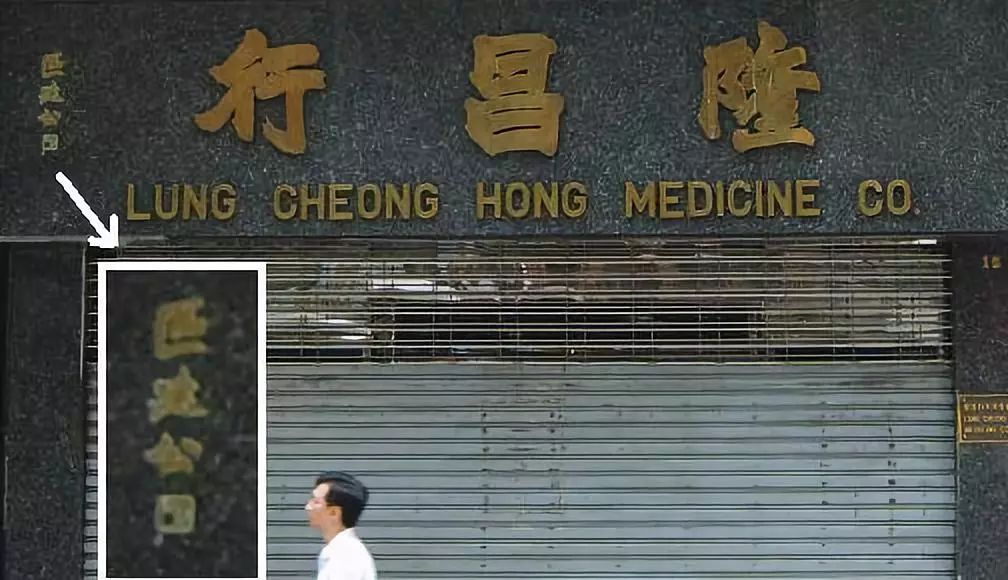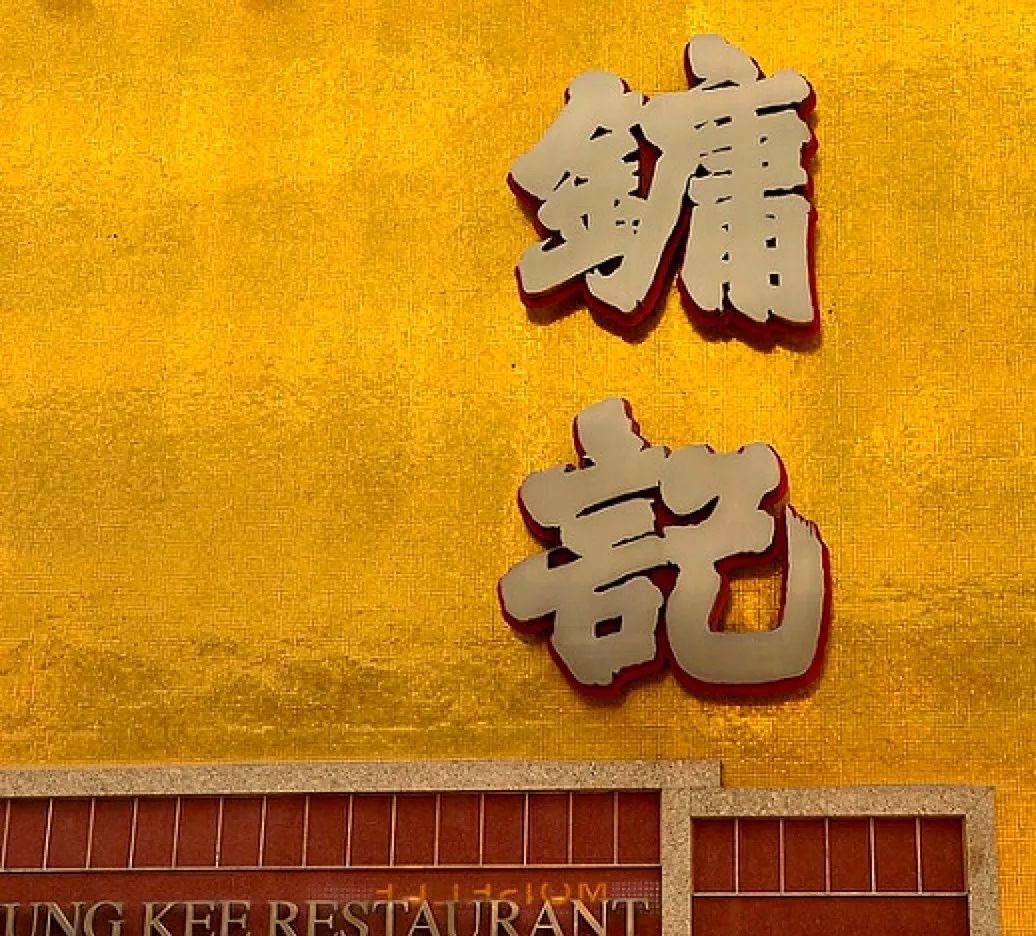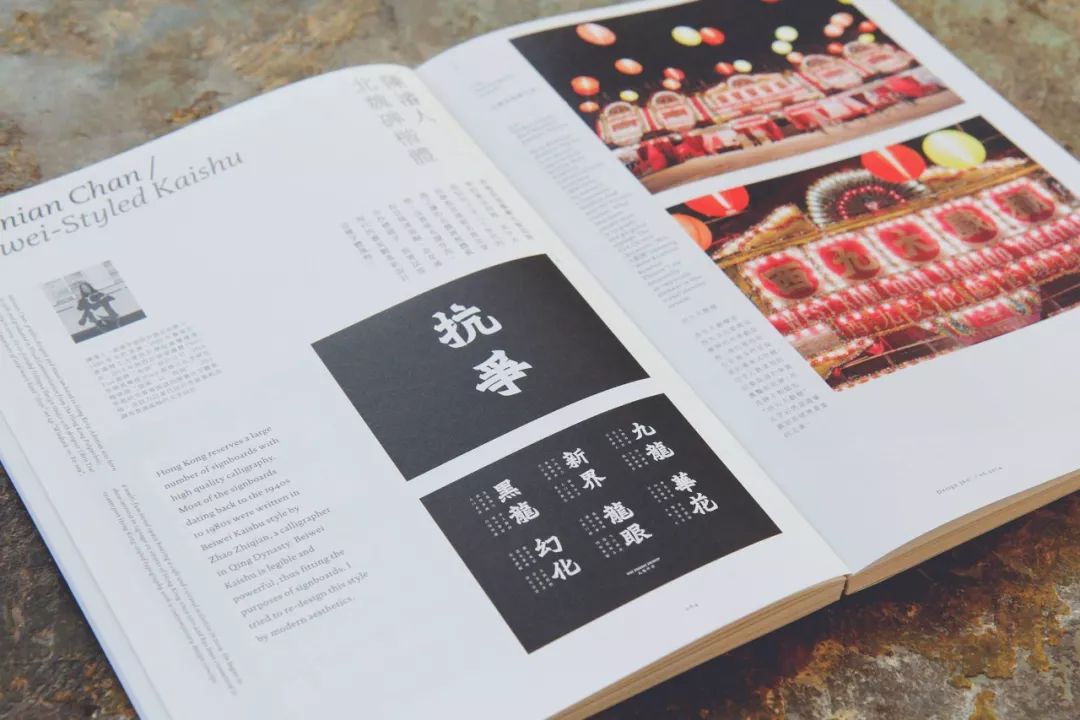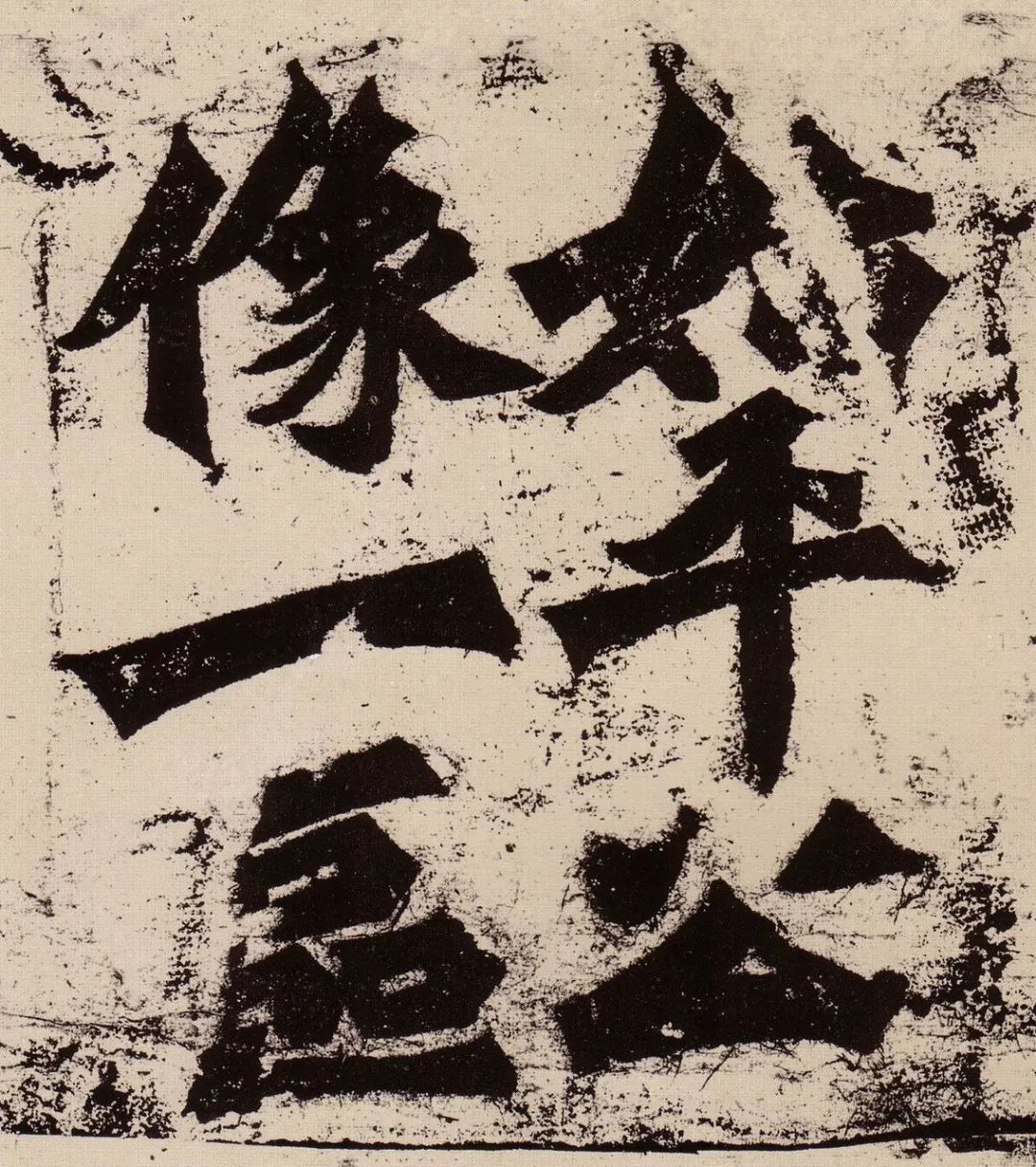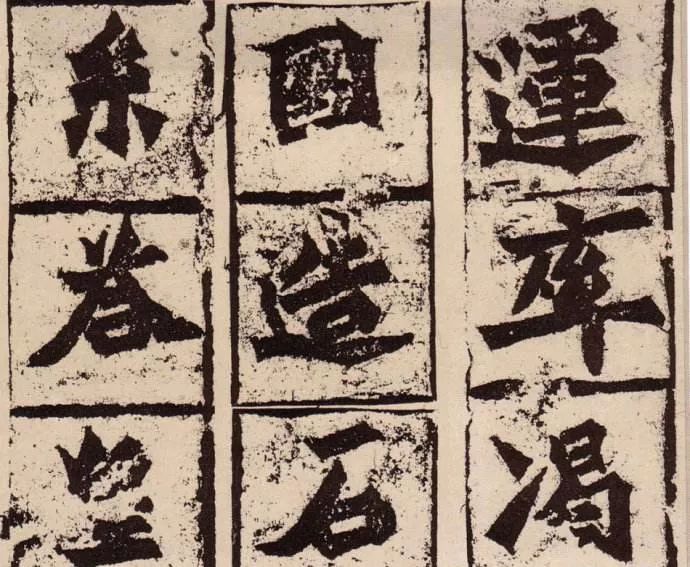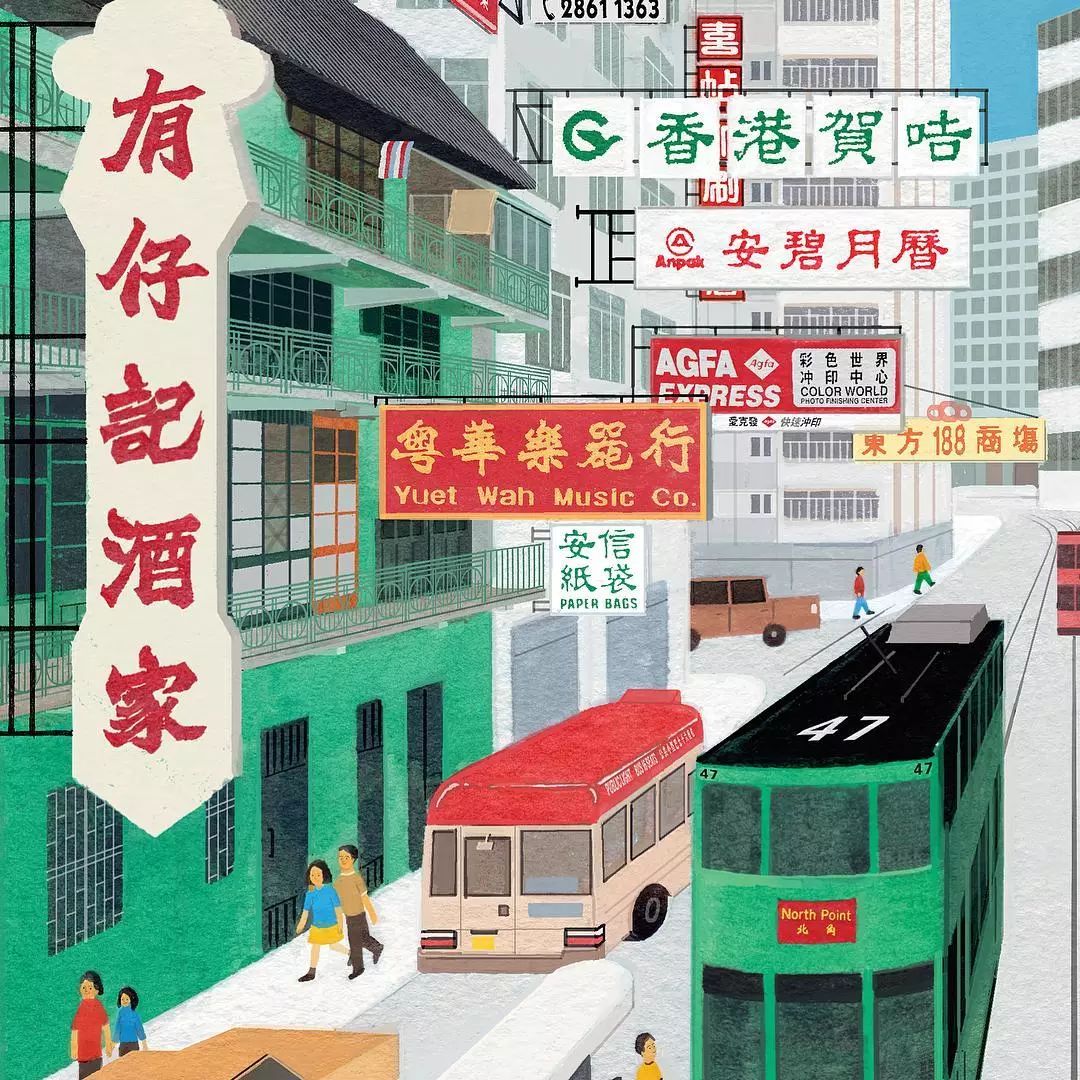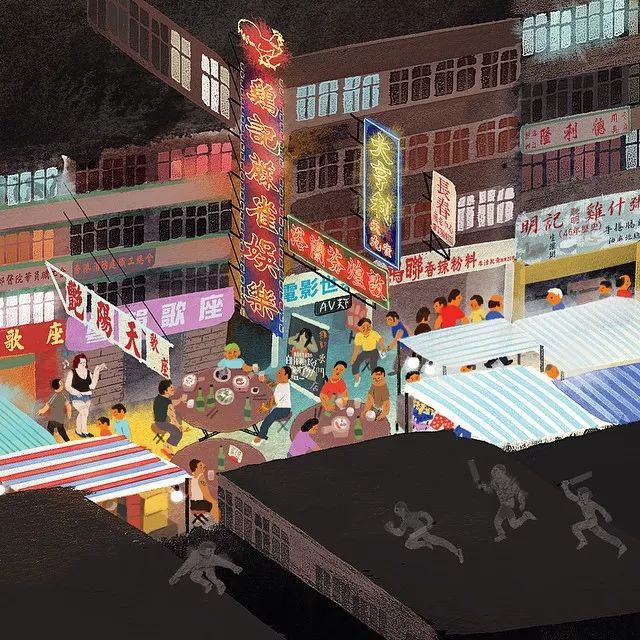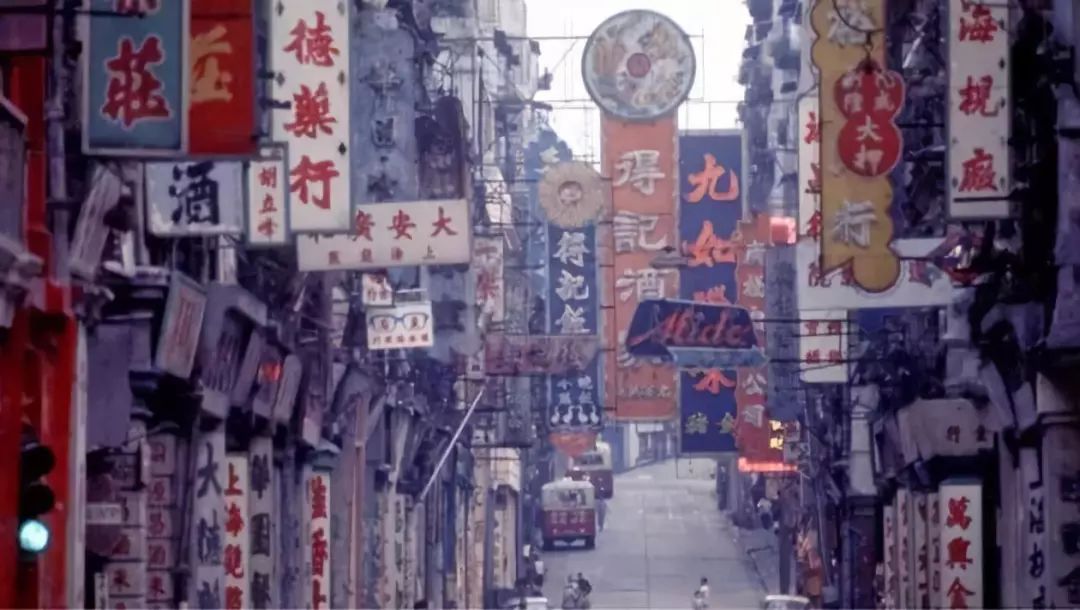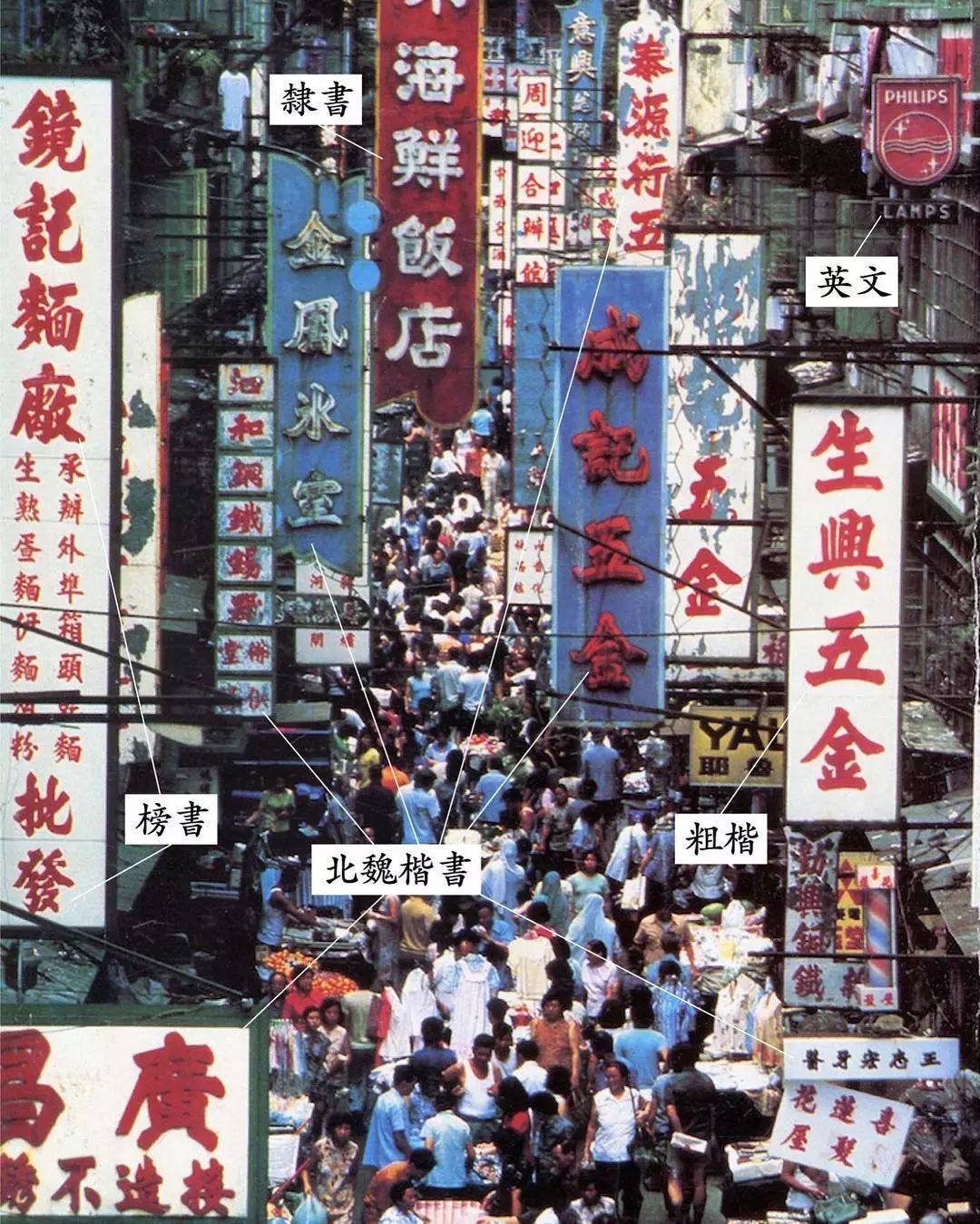
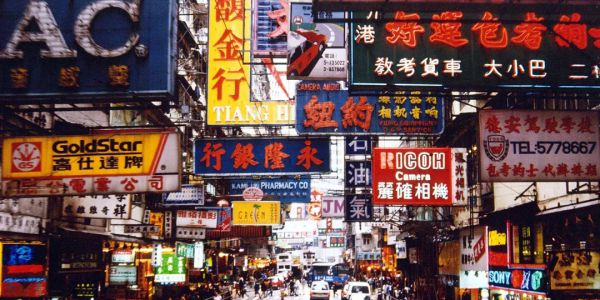
这种字体,曾经风靡了全香港
香港是招牌之都,当你在旧区四处张望,头上总有一两个书法、霓虹招牌。追根寻源,反寻到古字宝藏,香港独有的北魏楷书字体在街招上发扬光大,流传数十载,形成独有街头美学及庶民文化。如今,无处不在的笔迹随市区重建,老铺倒闭,工艺失传消失,不如跟惜古字如金的他们,展开一段字体救亡潮。
陈濬人:清朝赵之谦魏碑是写书法,区建公再将之变成招牌字,今天我以电脑加工,融入自己的风格,这就是字型设计最精妙之处。我们不是要怀旧,而是让字体于时代中重新演绎,新潮起来。
谭智恒:我们著重城市美学与文化,不是一昧旧,而是讲怎样传承这种逐渐褪色的文化。
北魏流行之根源
研究本地招牌及字型的理工大学设计学院助理教授谭智恒(Keith)以功用解释:香港人都是岭南人性格,实用主义为先,招牌字并不是纯美学,由于要远观,讲求辨认程度。
Keith指建筑物类型与街招数目有关,四十年代开始流行商住混合式大厦,当时人们都在里面单位搞小生意。当城市与街道密集,生意要从茫茫字海突围而出,就由字体、颜色入手,令招牌突然增多。
时代心态变
Adonian解释,从前的人很舍得花钱做招牌,写一个字约20元,约是一般人一星期薪水:那时的人做事较长线,认为生意是一世的,甚至传好几代,就算没钱都会关注招牌效果。反之现在经济转型,换画平常,讲求快狠准即食,时代心态间接令长看不厌的老手艺没落。
香港到处寻北魏
问Adonian字体的普及程度,他说由酒楼、西医、银行、饼家等各行各业都有:最著名是中环镛记,写得非常有气势,还有元朗好到底面家、太子凤城酒家、奇华饼家、创兴银行。虽然北魏楷书招牌在香港仍然随处可见,但新店舖已甚少采用书法字,令北魏字型日渐淡出。如今招牌较夸张,消费至上,较少人文气息,令北魏楷书书法招牌更弥足珍贵。
Adonian最喜欢镛记招牌二个字。一般楷书的「言」字两横长度相若,镛记的「记」字则刻意加长第二横,以及强调牵丝,令原本平淡的「言」字更跃动。倔强的竖弯鈎是赵之谦风格的一大特征,区建公及香港风格则将之改良,转折用中锋令整个笔划平稳。
从前招牌上的书法字体直接用极粗毛笔书写,再勾画外框然后立体切割出来。比起现在先在电脑用预设字体设计好再放大,传统书法更能切合视觉尺寸上的要求更有美感。
走在街上,我们总是纯粹地把街道招牌、广告标语等文字当成传意工具,却忽略了在身边的文字,都有其一套的美学。香港北魏真书,是华文世界里特有的书体,相信大家都不会陌生。
但到底为什麽叫「香港北魏真书」?
这要从南北朝开始讲起。魏晋南北朝时期,由于社会动荡不安,书法亦分为南北两派。所谓「北碑南帖」;北派的书体,有着汉隶的风格,因为以碑刻为主,所以字形看上去大多朴实方正,笔画钝角分明的十有八九就是魏碑体。而后来很多书法家比如说欧阳询,褚遂良都受其影响,作品里也会有着北魏的味道。而「真书」又名楷书或正书,是三国时期的一个称呼,现在已经很少人这样叫。因此,「北魏真书」就是介乎与隶书跟楷书之间的书体。
北魏始平公造像记|公元498年
那么为什么旧香港会有这
么多北魏的招牌?
很简单四个字:今期流行
当时香港有位书法家叫区建公先生(1887 - 1971),他可是现在北魏真书招牌的开山始祖。他为店铺题字的时候,优先考虑的不是书法艺术的美学,而是阅读的实用性。因为北魏体的起笔、收笔和转折处都比较分明,适合远距离阅读,而且容易辨认。这个实用想法今天却造就了一种文字的美学,和岭南人实事求是的精神不谋而合。
1950开始 区建公擅长于赵之谦雄浑的北魏体。五、六十年代期间,区建公常以北魏体为商店写招牌,令北魏招牌于当时大行其道,不同行业都採用此字体。如「奇华饼家」、「公和玻璃镜器」等都出自他手。区建公非常多产,沿著中上环找到不少他题字的招牌。他写得很有个人风格,发展出招牌北魏体。